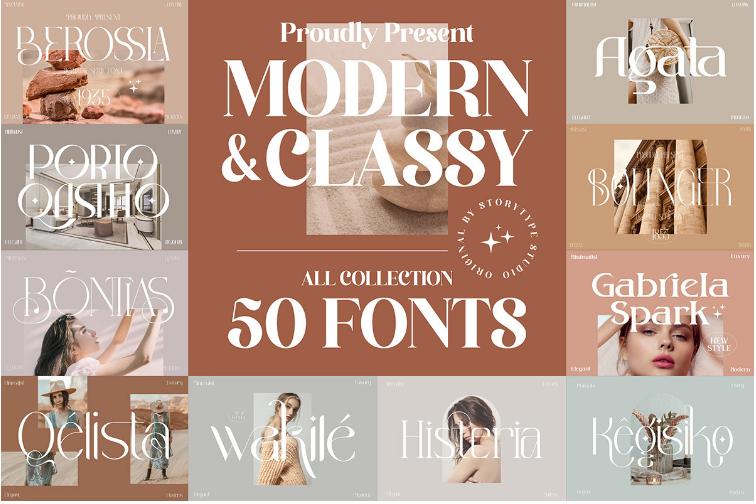
[Creativefabrica] Professional Modern Serif Font Bundle (storytypestudio)
Набор профессиональных современных шрифтов с засечками.
В этом пакете собраны 50 элегантных и современных шрифтов с засечками, которые вы можете использовать в своих будущих проектах, включая дизайн логотипов, канцелярские принадлежности, плакаты, посты в социальных сетях и многое другое.